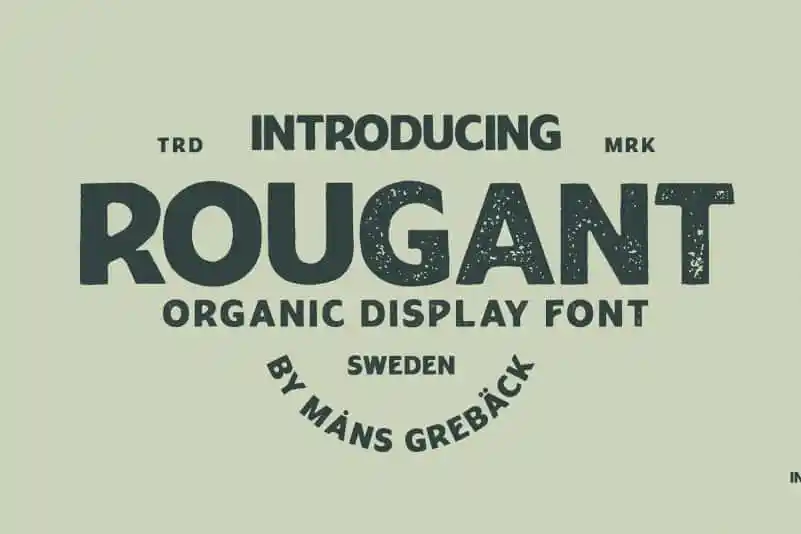
A Rougant Display Font é uma novidade entre as fuentes de tipo à sans serif inspirada nos anúncios retro de 70 anos, nas letras musicais e nos filmes do mesmo período. Seu design remete a um estilo rock n’ roll vibrante, criado para dar vida a logos de motocicletas ou qualquer projeto gráfico que deseje transmitir uma atmosfera animada e divertida. Essa fonte é perfeita para criar identidades visuais com o tom assertivo e forte característico do movimento musical, oferecendo um design clean e moderno, sem perder a personalidade marcante dos anos 70. Engaje-se no universo da Rougant Display Font e deixe que seu projeto brilhe em destaque ao adotar esta fonte elegante e vibrante.